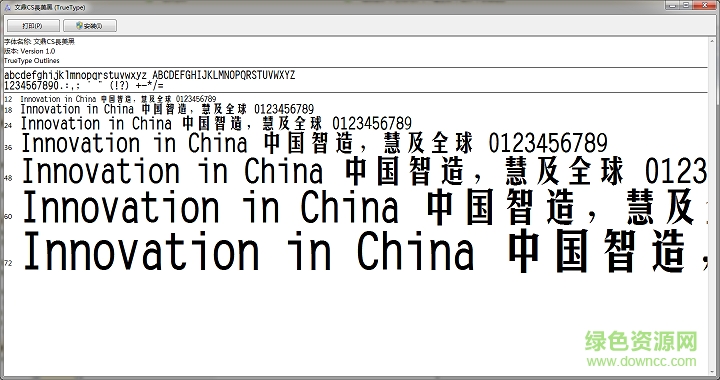
chunmeiheicseg字體又叫文鼎CS長美黑字體,是一款修長型的黑體字體,優(yōu)雅美觀又實(shí)用,還富有古典藝術(shù)氣息,也是大多數(shù)用戶在進(jìn)行書面內(nèi)容排版時(shí)比較常用的字體之一,非常的端莊整潔,喜歡這類字體的小伙伴快來綠色資源網(wǎng)下載吧!
chunmeiheicseg字體特點(diǎn)
它具有字體勻稱、清秀美觀的特點(diǎn),給人端正又正氣的視覺效果,可適用于標(biāo)題類文字輸入。